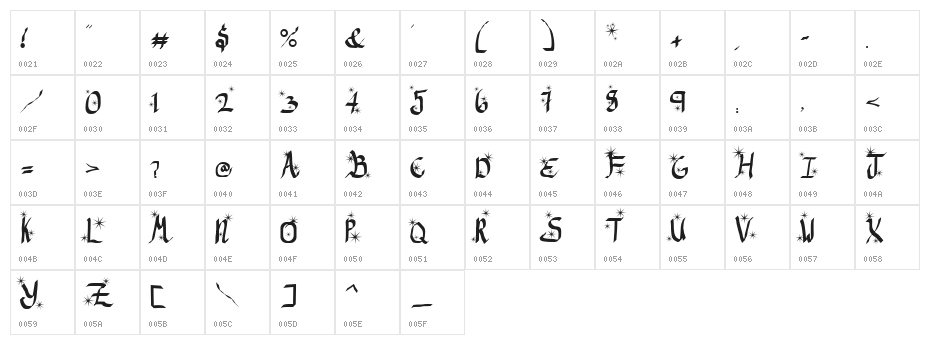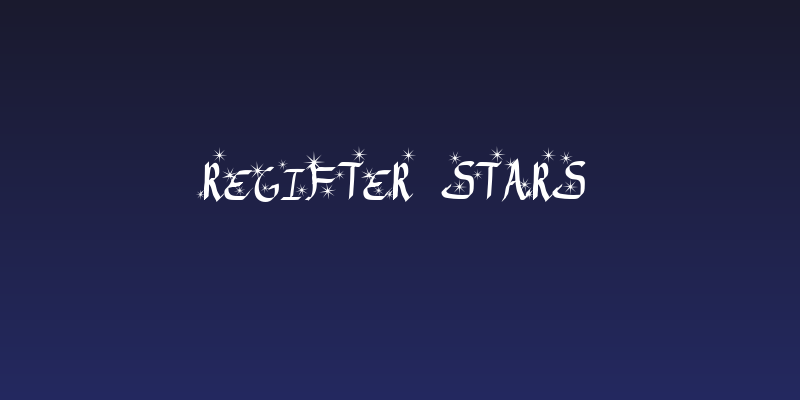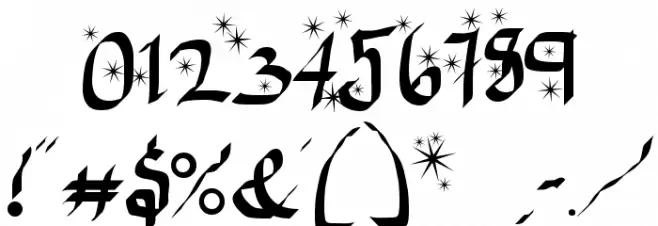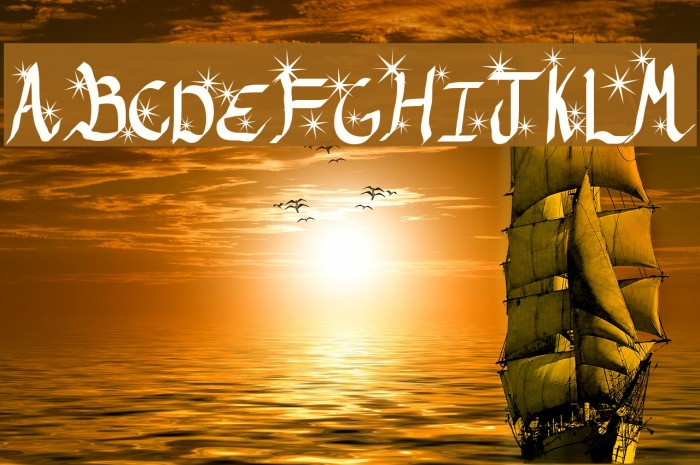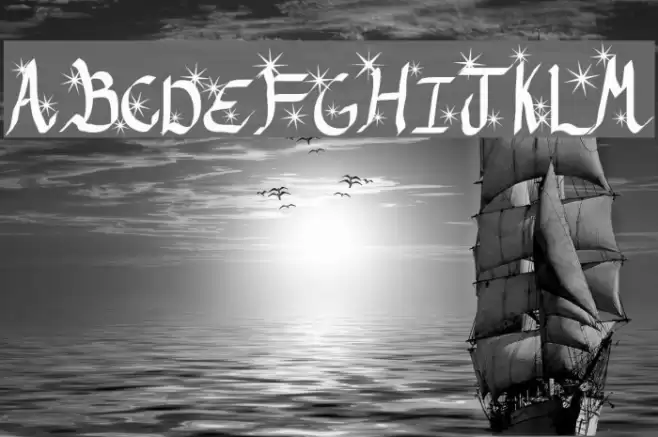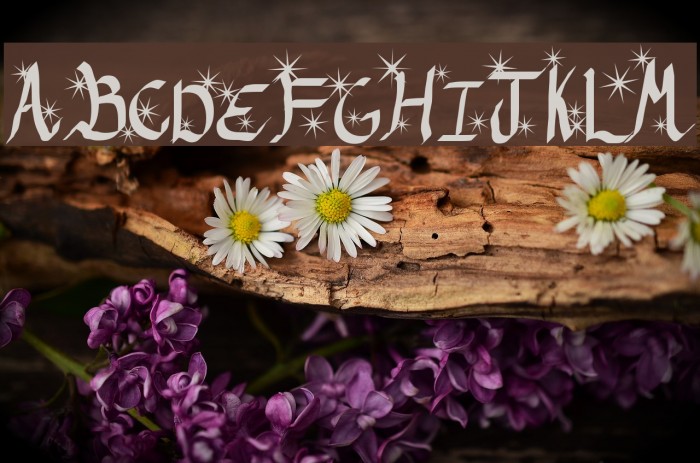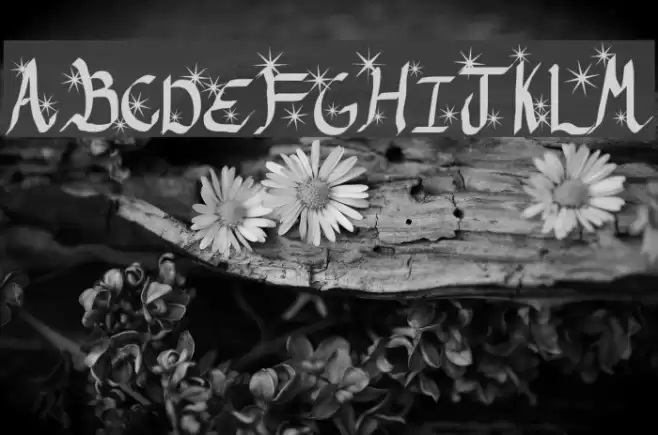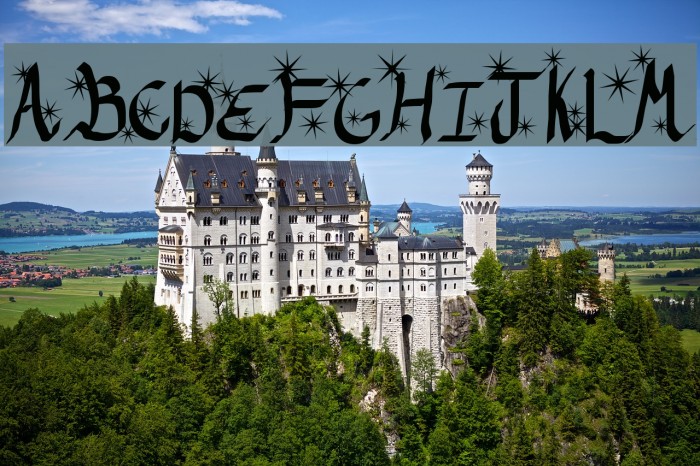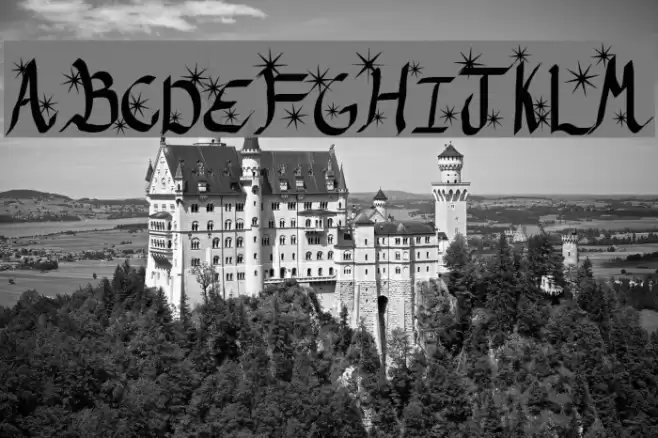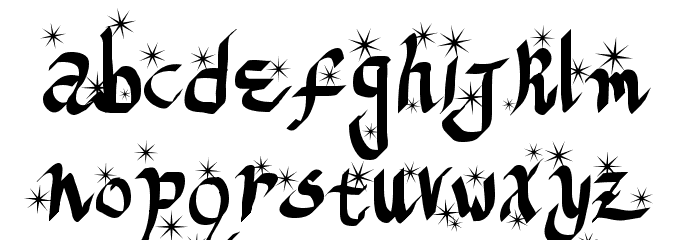
ReGifter Stars Font
| Cas d'utilisation | Headlines, Logos, Invitations |
| Projets proposés | Ideal for holiday cards, party invitations, festive posters, and playful branding projects. |